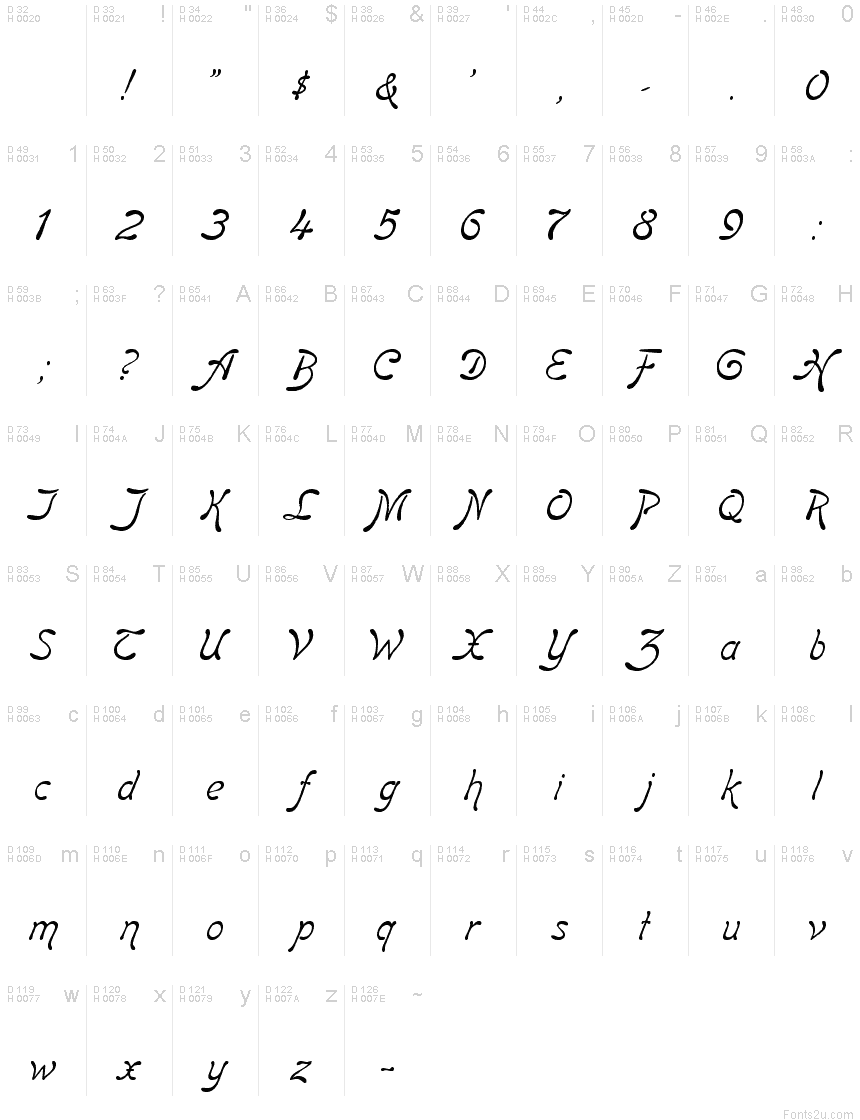
Boomerang Italic od Harolda Lohnera to darmowy, kaligraficzny krój pisma inspirowany klasycznymi krzywiznami Art Nouveau. Zapętlone pociągnięcia, łagodne pochylenie i żywy rytm nadają tekstowi poczucie ruchu, przypominając tusz nakreślony pewną, ciągłą linią. Litery są gładkie i elastyczne, z figlarnymi zakończeniami, które ożywiają formę słów, nie utrudniając przy tym czytania.
Dzięki Boomerang Italic nadasz ciepły i wyrazisty charakter logotypom, identyfikacji wizualnej butików, opakowaniom, plakatom, zaproszeniom, nagłówkom oraz grafikom w mediach społecznościowych. Ten darmowy font najlepiej sprawdza się w większych rozmiarach, gdzie jego zamaszyste formy i subtelne detale mogą w pełni wybrzmieć. Aby uzyskać zrównoważony układ, połącz go z prostym krojem bezszeryfowym w tekście uzupełniającym i pozwól Boomerang Italic przejąć najbardziej charakterne momenty.